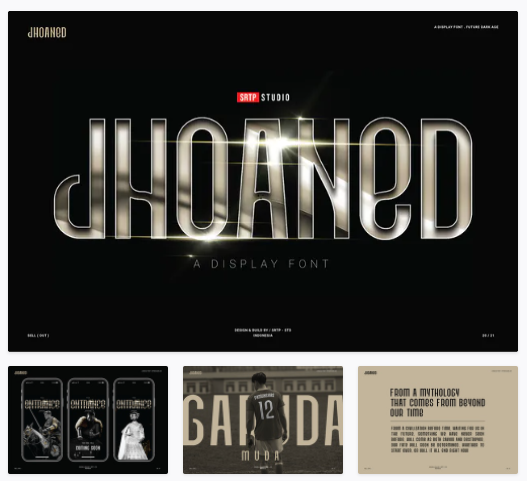
[Elements.Envato] ISC JHOANED Font (2021)
JHOANED - это дисплейный шрифт.
Этот шрифт идеально подходит для вывесок, логотипов, названий фильмов, заголовков, обложек книг, пивных этикеток, упаковки, принтов или чего-то еще.